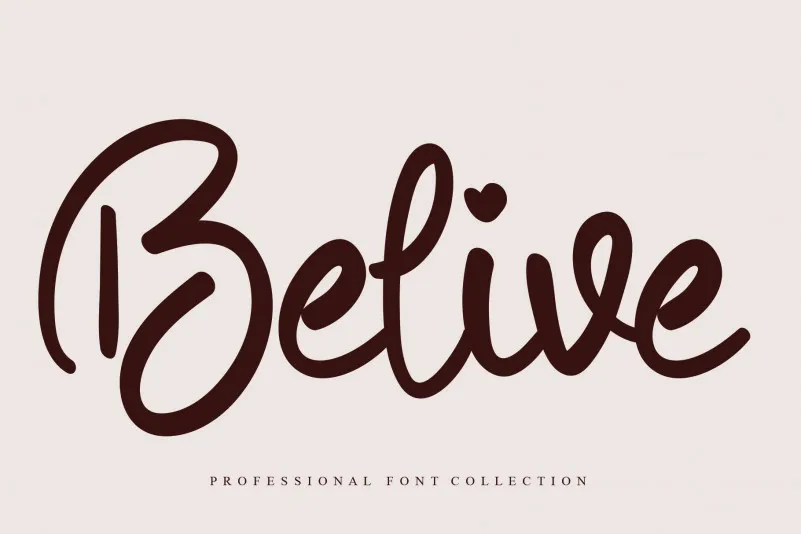
A Belive Script Font é uma escolha perfeita para quem busca personalidade em seu design digital. Se você está procurando por uma tipografia com um toque especial e criativo, essa pode ser a solução que você precisa. Com linhas levemente desenhadas e traços delicadamente curvados, a Belive Script é ideal para criar textos de marca distintivos ou até mesmo artes gráficas memoráveis. Estamos ansiosos para oferecer uma experiência excepcional aos nossos clientes com a Belive Script Font. Ela foi criada para dar vida à sua ideia, tornando-a única e impactante no mundo digital contemporâneo. Seja você um designer profissional ou um entusiasta de design que busca algo novo e desafiador, a Belive Script não deixará você desapontado. CriativaLetter é responsável pela criação desta fonte especial, que oferece uma abordagem moderna e original à tipografia. A fonte traz características únicas que podem dar um gás à qualquer projeto visual, seja ele para materiais de marketing ou elementos de design gráfico. Além do seu apelo criativo, a Belive Script também é fácil de integrar em projetos variados. Sua simplicidade e elegância permitem que ela se destaque enquanto mantém um equilíbrio perfeito entre clareza e sensibilidade, tornando-a uma opção versátil para qualquer aplicação visual. Descubra por si mesmo o poder da Belive Script Font e transforme sua marca ou projeto em algo realmente inovador. Não hesite em experimentar – você não vai se arrepender de ter dado um passo adiante no seu design.